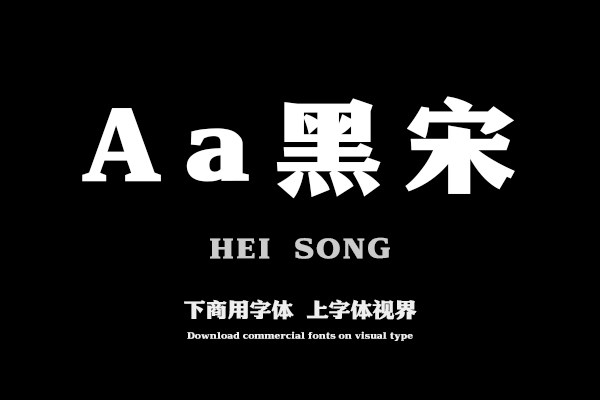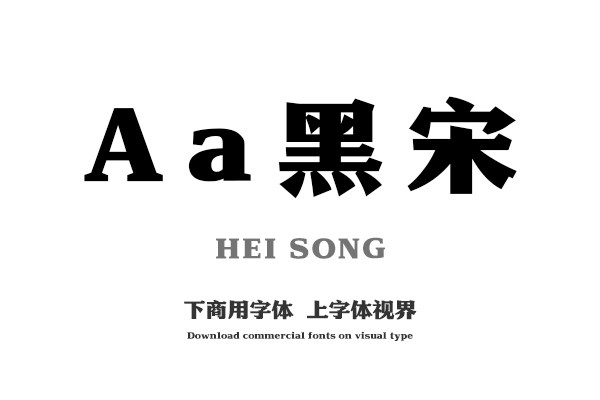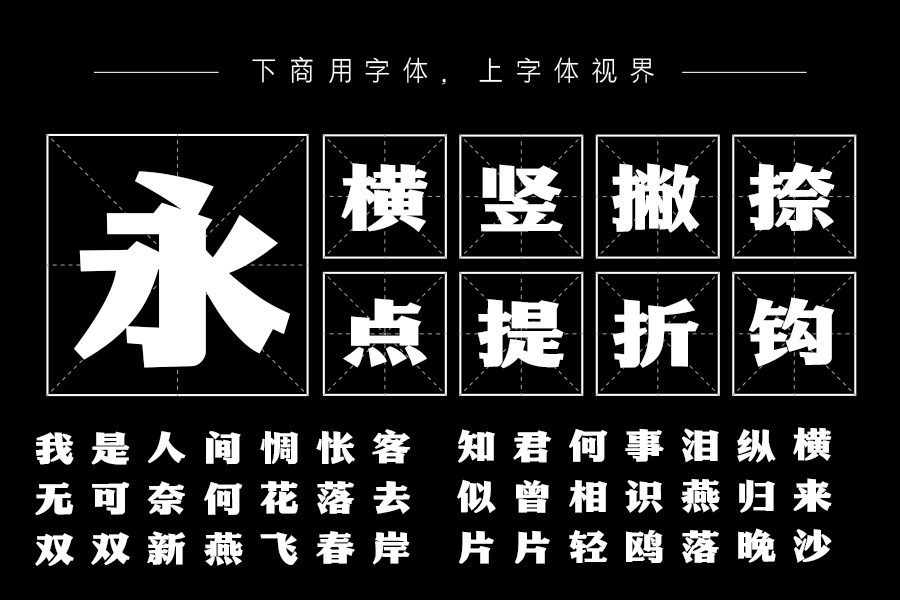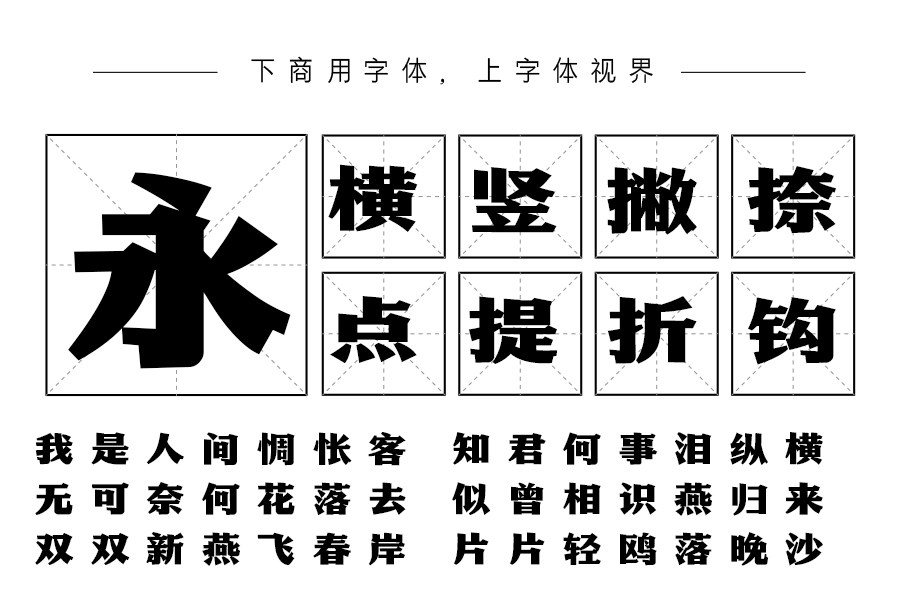
结合黑体和宋体的设计特征,设计一款特征突出的标题字体。宋体衬角加上粗细对比弱化的黑体气质,使这款字醒目有力而不乏细节。购买须知:“下载服务费”与“字体VIP”所获得字体 仅用于个人非商用, 商用请联系付费授权。本字体为电脑用字,手机没有root权限不支持直接手机换字(手机如何root,请自行百度搜索教程)。购买前请先 了解清楚后再付款 ,字体为虚拟产品无法回收 一旦购买不支持退款。